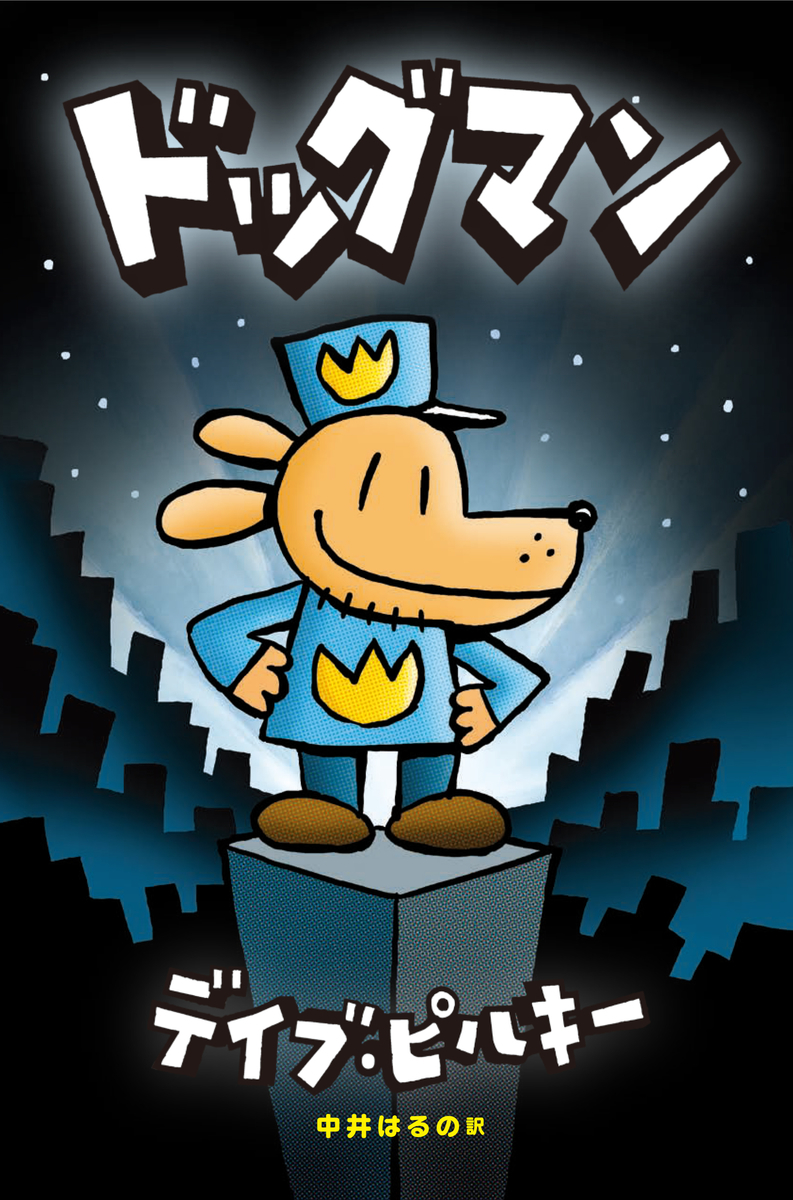
ドッグマン
飛鳥新社は全米人気No.1児童書でデイブ・ピルキー氏著書の「ドッグマン」1巻を2019年4月24日に発売した。
デイブ・ピルキーProfile●子どものころ多動性障害(ADHD)、ディスレクシア、行動障害だった。授業の邪魔ばかりしたため、先生たちは毎日、デイブを廊下に出した。幸いにも、デイブは絵をかくこと、物語を考えることが大好きだったので、廊下で自作の漫画を作っていた。2年生のとき、パンツマンが主人公のマンガを描くと、デイブの先生はそれを破りすて、こんなバカらしいものをかいて一生を送れるわけがないといった。
幸いにもデイブは先生のいうことをぜんぜんきかなかった。
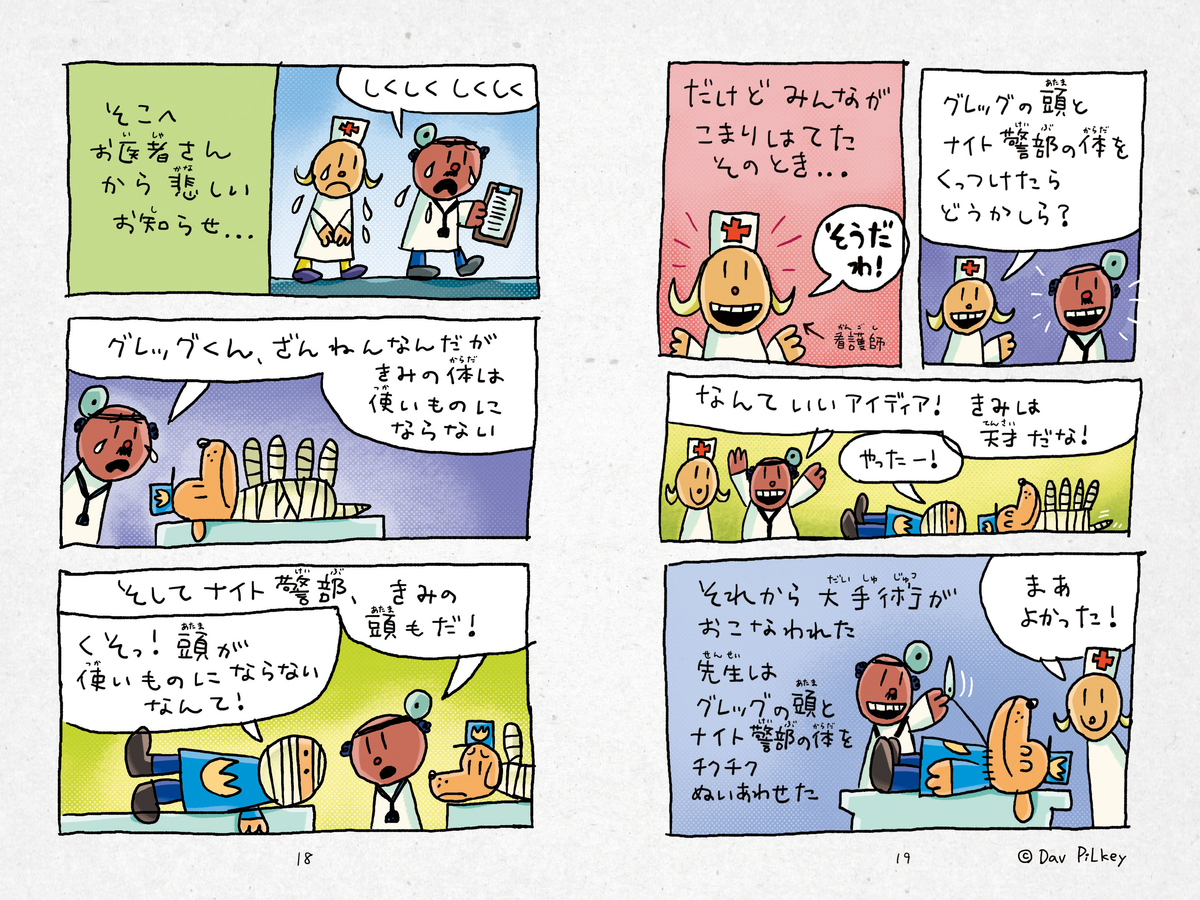
アメリカでの人気ぶりがとにかくすごい「ドッグマン」
アメリカではこれまでに6巻まで発売され、累計2,300万部、最新の6巻は初版だけで500万部という桁外れの人気ぶり。ニューヨークタイムズのベストセラーランキングでは、「児童書シリーズ部門」で2019年1月から1位を独走中。
「ドッグマン」人気の秘密
〇「絵本と本のあいだ(ブリッジブックス)」として圧倒的な支持。読み聞かせをしてもらう絵本から、自分で読む本へ移る「最初の1冊はドッグマン」と定着している。オールカラーのコミック形式で親しみやすく、無理なく物語を追える本書。240ページの厚さの本がスイスイ読めてしまい、自信がつく。
〇小学生がノートに描いた落書きが、そのまま本になったみたいな、絵もセリフの文字も、まるで子どもが描いたよう。お子さんにとっては親近感をもって読むことができます。
〇楽しい仕掛けがいっぱいで、パラパラマンガや似顔絵の描き方コーナーなどただ読むだけでなく「本で遊べる」工夫が満載。
「ドッグマン」とアメコミブームとの関係
マーベル作品やDC作品など、アメコミが日本でも絶好調で、「ドッグマン」もジャンルとしてはグラフィックノベルと呼ばれるジャンルになっている。つまり、ドッグマンはただの児童書ではなく、子供が最初に親しむアメコミでもある。
「ドッグマン」の著者は発達障害だった
著者のデイブ・ピルキー氏は子どものころADHD、ディスレクシアでしたが、好きなマンガに打ち込んで才能を伸ばした。教育現場でも発達障害の子供を得意な才能を伸ばすような指導をするようになってきており、そのうまくいった例でもある。
「ドッグマン」日本でもブームの兆し
日本でも人気YouTuberがタイアップ動画を公開している効果もあり、ブームの兆し!読者ハガキでは、連日、読者のマンガやイラストの力作が届いている。
全米人気ナンバーワン児童書が日本上陸!
アメリカでは6巻まで発売され、累計2300万部。
最新刊はなんと初版部数500万部!
ニューヨークタイムズ・ベストセラー「児童書」1位に君臨!
最強のスーパーヒーローがあらわれた!
その名は、ドッグマン !
屈強だけどおバカな警官と、頭はいいけど体が弱い警察犬。
その警官のカラダと警察犬のアタマがくっついて!?
最強のヒーロー「ドッグマン」が、
悪の宿敵「猫のピーティー」と繰り広げる
ハラハラドキドキの物語!
児童書翻訳のスペシャリスト 中井はるのさんが太鼓判!
『グレッグのダメ日記シリーズ』『ワンダー』を翻訳している
ナンバーワン児童書翻訳家の中井さんが翻訳。
「本当によくできていて面白い」と太鼓判。
「子どもが描いている」本だから、子どもが喜ぶ! 「小学生が描いたマンガ」という世界観の本書、
絵も字もまるで子どもがノートに書いたよう。
日本版の描き文字は、『ダース・ヴェイダーとルーク(4才)』も
手掛けたヤギワタルさんの名人芸です。
絵本から本へ。その最初の1冊にも最適!
マンガでも厚い本を1冊読むと、お子さんに自信がつきます。
カンタンで、面白くって、スイスイ読める本書をおすすめします。
たのしいオールカラー240ページ!